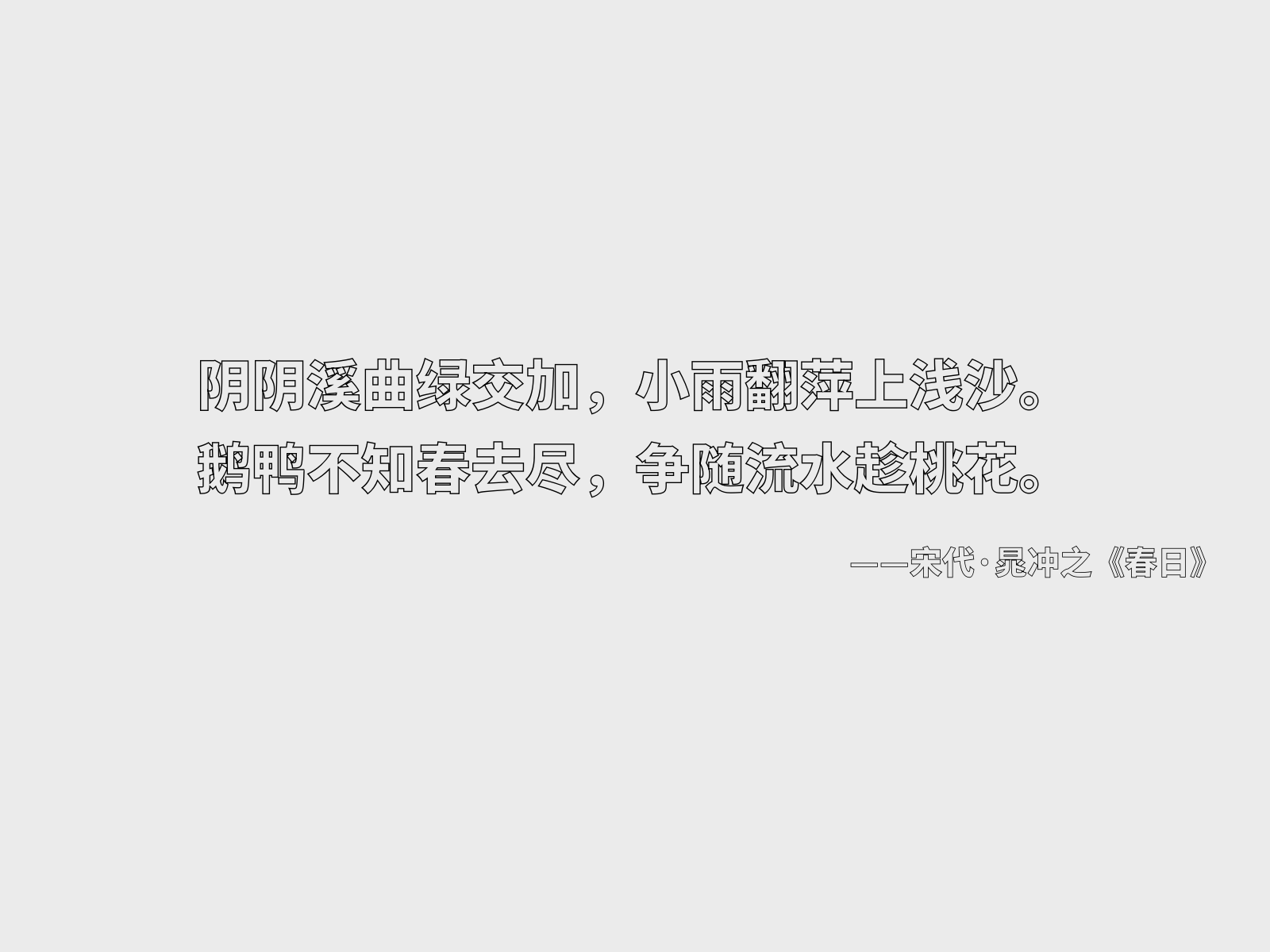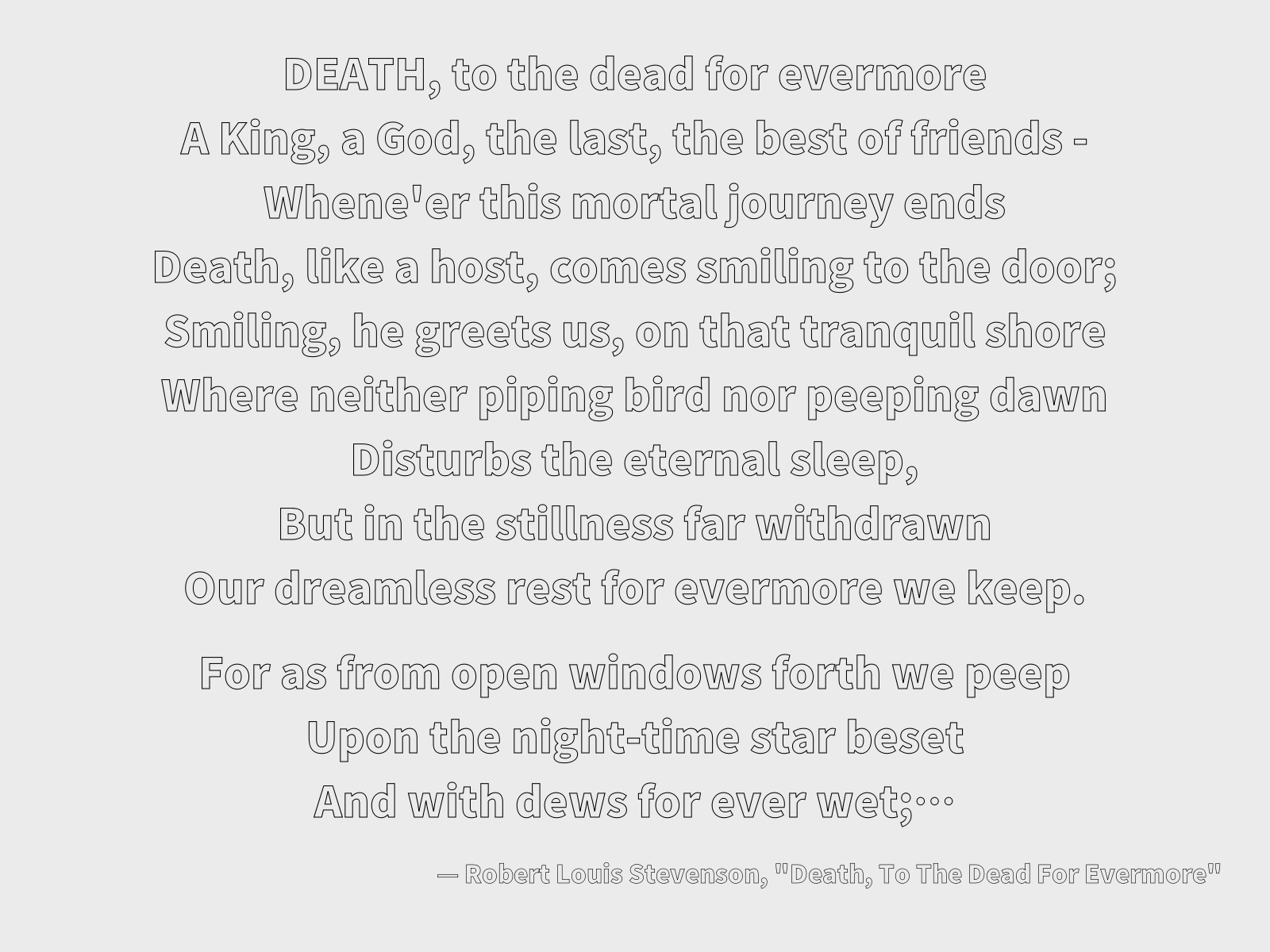
空源黑体,本质上是一款基于思源黑体Heavy进行空心化处理的字体。它专门提供了Light、Regular、Medium这三种不同的字重选择。开发这款字体主要是为了解决在Keynote这类演示软件,或者其他一些无法直接渲染空心字体效果的工具中,用户想要使用醒目空心字形时的痛点。此前虽然也存在像“如源拔黑体”这样的空心字体方案,但它们在实际使用中常常会出现中文字符显示不全或缺字的情况。因此,才诞生了这个新的版本,它确保了对简体与繁体汉字的完整支持,能够稳定、无缺漏地呈现所有字形。这款字体依据SIL Open Font License 1.1协议免费向公众提供。如果您想了解协议的具体内容、可以做什么、不可以做什么以及相关的免责条款等详细信息,请务必查阅随字体提供的完整License授权文件。